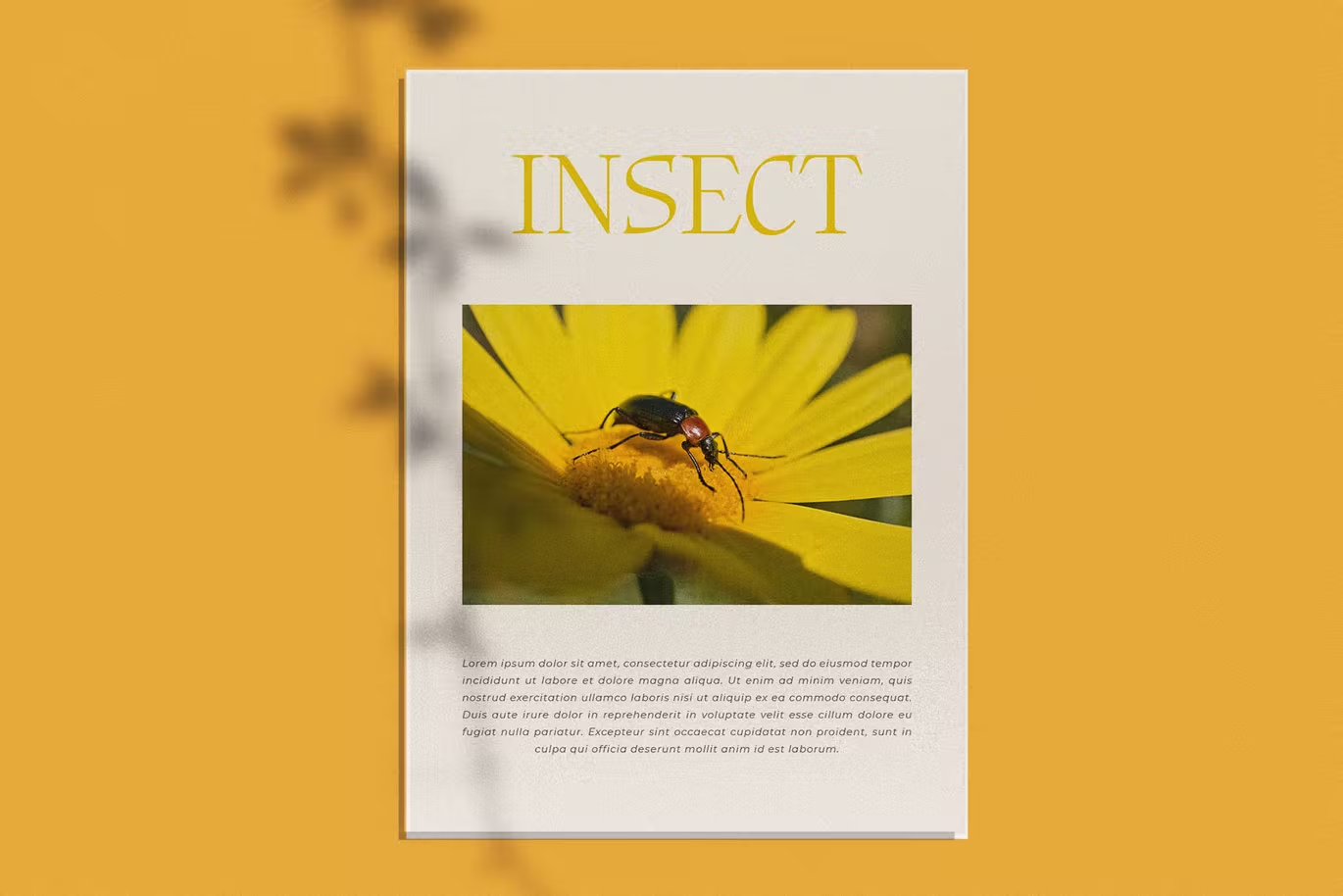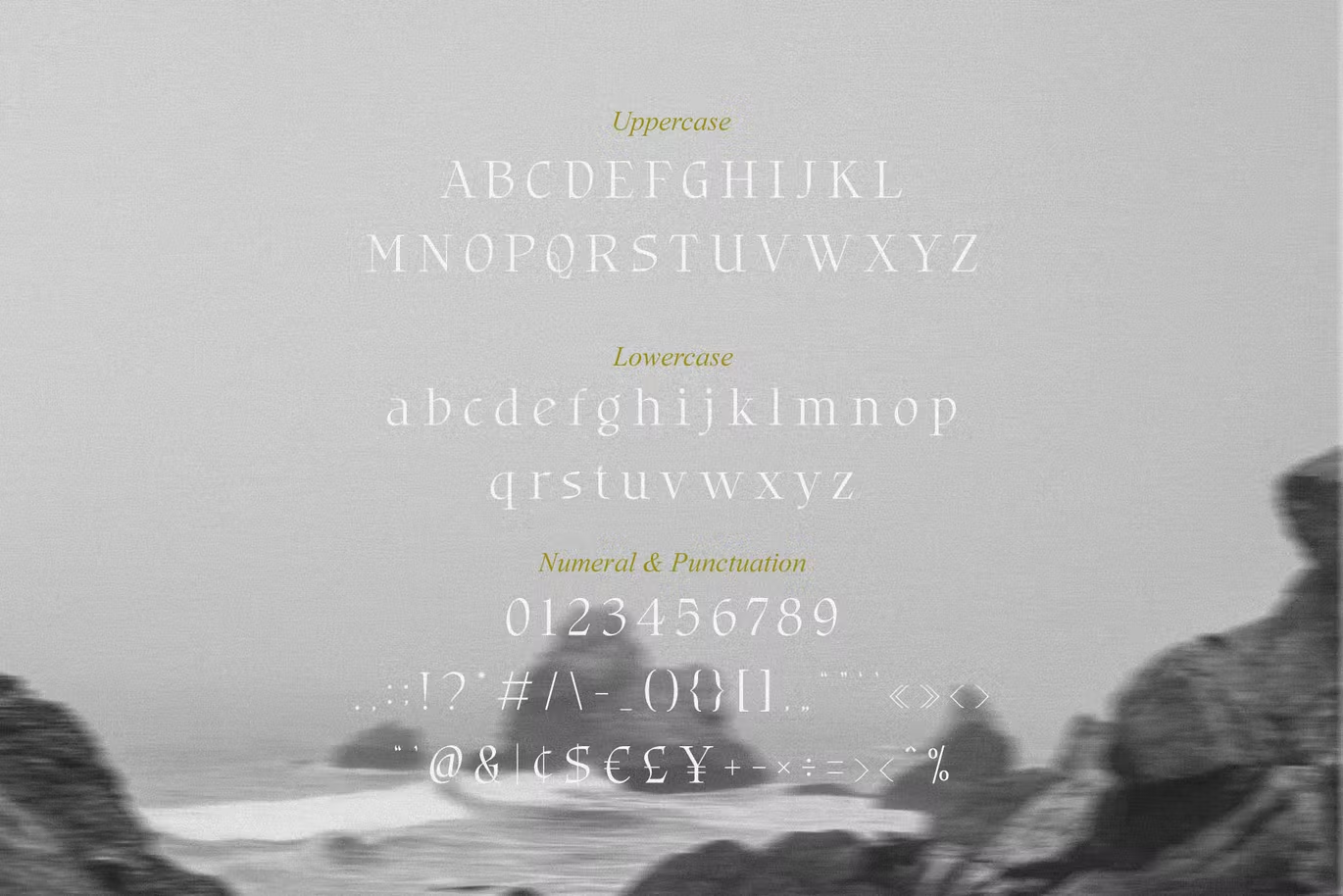
Bligra Modern Serif Typeface
Description de Bligra Modern Serif Typeface
Présentation de la police Bligra Modern Serif. Bligra est une police de caractères moderne et élégante, idéale pour afficher les titres, les logos, l’image de marque, les magazines, les emballages de produits et les invitations. Bligra est doté de lignes épurées et de courbes douces qui donnent à tout projet une touche supplémentaire de classe.